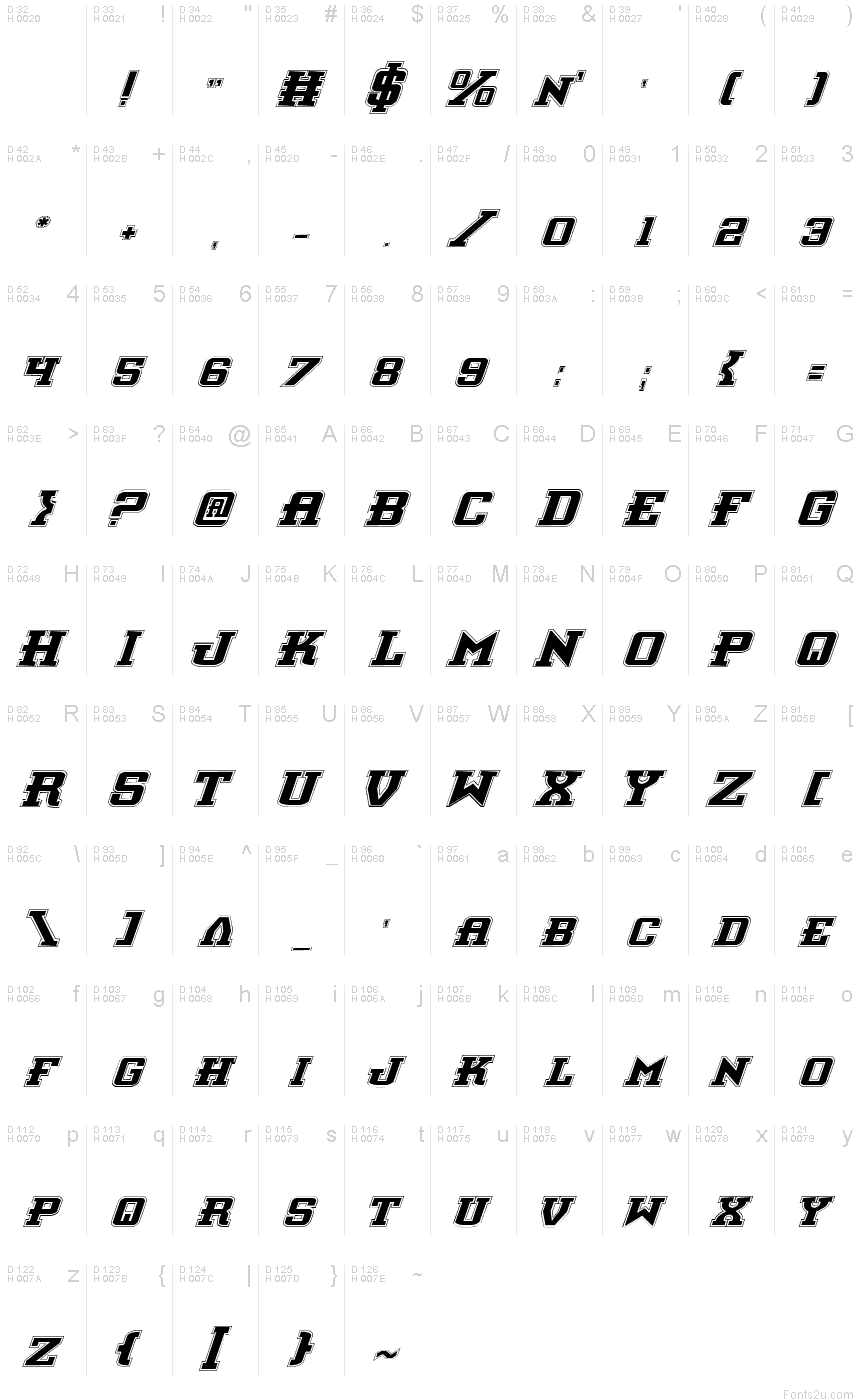
Interceptor Pro Italic von Iconian Fonts ist eine kostenlose, kursive Display-Schrift im Athletic-Stil, die die Dynamik und das Selbstbewusstsein von Vintage-Sport-Typografie einfängt. Die Großbuchstaben sind stark geneigt und bestehen aus massiven Blockformen mit scharfen Ecken und einer doppelten Kontur – das sorgt für diesen „Jacket-Patch“- und Team-Banner-Look statt eines glatten, modernen Stils.
Sie passt perfekt auf Plakat-Überschriften, E-Sport-Branding, Schulveranstaltungen, Trikot-Merch und Titelkarten, bei denen eine kostenlose Schrift Dynamik braucht, ohne an dieser kraftvollen, emblematischen Wirkung einzubüßen. Ideal, wenn kurze Namen, Cover-Zeilen oder Monogramme wettbewerbsorientiert und wie „gestempelt“ wirken sollen, denn die konturierten, nach vorne geneigten Buchstaben bringen diese mitreißende Energie von Haus aus mit.